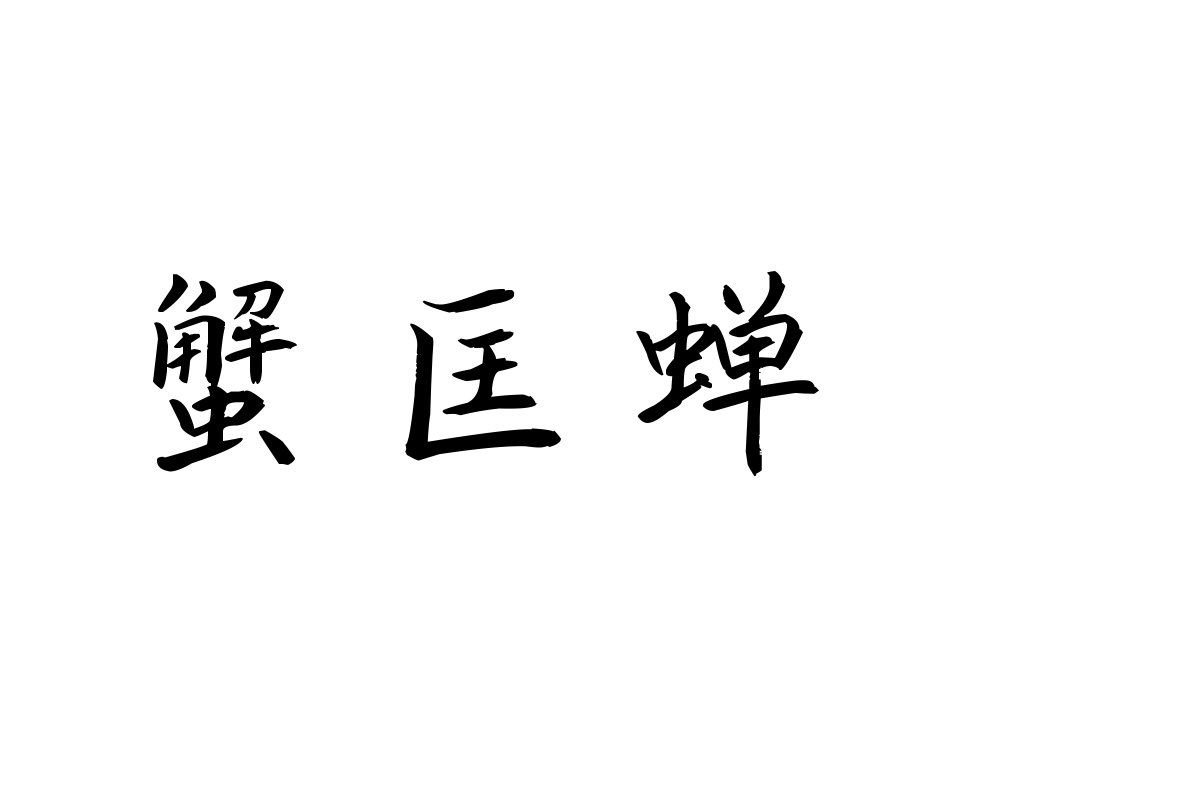
汉呈王天喜毛笔手写字体,是汉呈王天喜先生在20世纪80年代创作的一款具有浓厚中国传统风格的书法字体。这款字体以其独特的笔触、结构和韵味,深受广大书法爱好者的喜爱。
汉呈王天喜毛笔手写字体的特点如下:
1. 笔画流畅:汉呈王天喜毛笔手写字体的笔画流畅自然,线条粗细变化丰富,既有刚劲有力的线条,又有柔和细腻的线条。这种流畅的笔画使得书写者可以更好地表达自己的意图和情感。
2. 结构严谨:汉呈王天喜毛笔手写字体的结构严谨,每个字的笔画都经过精心布局,使得整个字形呈现出一种和谐统一的效果。这种严谨的结构使得字体具有很高的辨识度和美感。
3. 韵味十足:汉呈王天喜毛笔手写字体具有很强的韵味,无论是楷书、行书还是草书,都能展现出独特的风格和魅力。这种韵味使得书写者可以在书写过程中感受到一种愉悦和满足感。
4. 艺术性强:汉呈王天喜毛笔手写字体具有较强的艺术性,不仅适合作为书法作品的创作,也适合作为装饰画、名片等商业用途。这种艺术性使得汉呈王天喜毛笔手写字体具有较高的市场价值。
总之,汉呈王天喜毛笔手写字体是一款具有深厚文化底蕴和艺术价值的书法字体,值得书法爱好者收藏和欣赏。